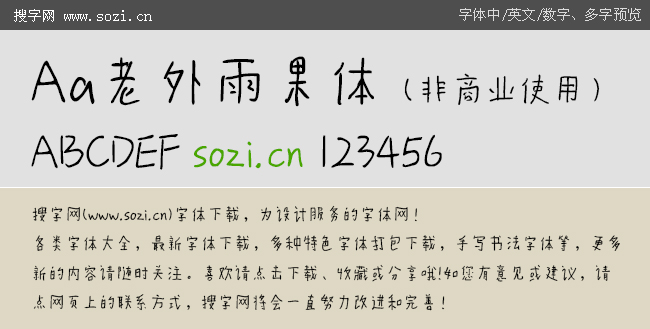
Aa老外雨果體
搜字網(wǎng)給大家提供一款A(yù)a老外雨果體(非商業(yè)使用)中文字體下載,Aa老外雨果體是一款卡通風(fēng)格的手寫字體,這款字體字形稚嫩可愛,充滿童趣,具有很好的視覺感。適合應(yīng)用于藝術(shù)設(shè)計(jì)、平面宣傳設(shè)計(jì)、網(wǎng)頁設(shè)計(jì)、海報(bào)設(shè)計(jì)等應(yīng)用(此字體為個(gè)人非商用版,商用可以聯(lián)系QQ:1006760504)。